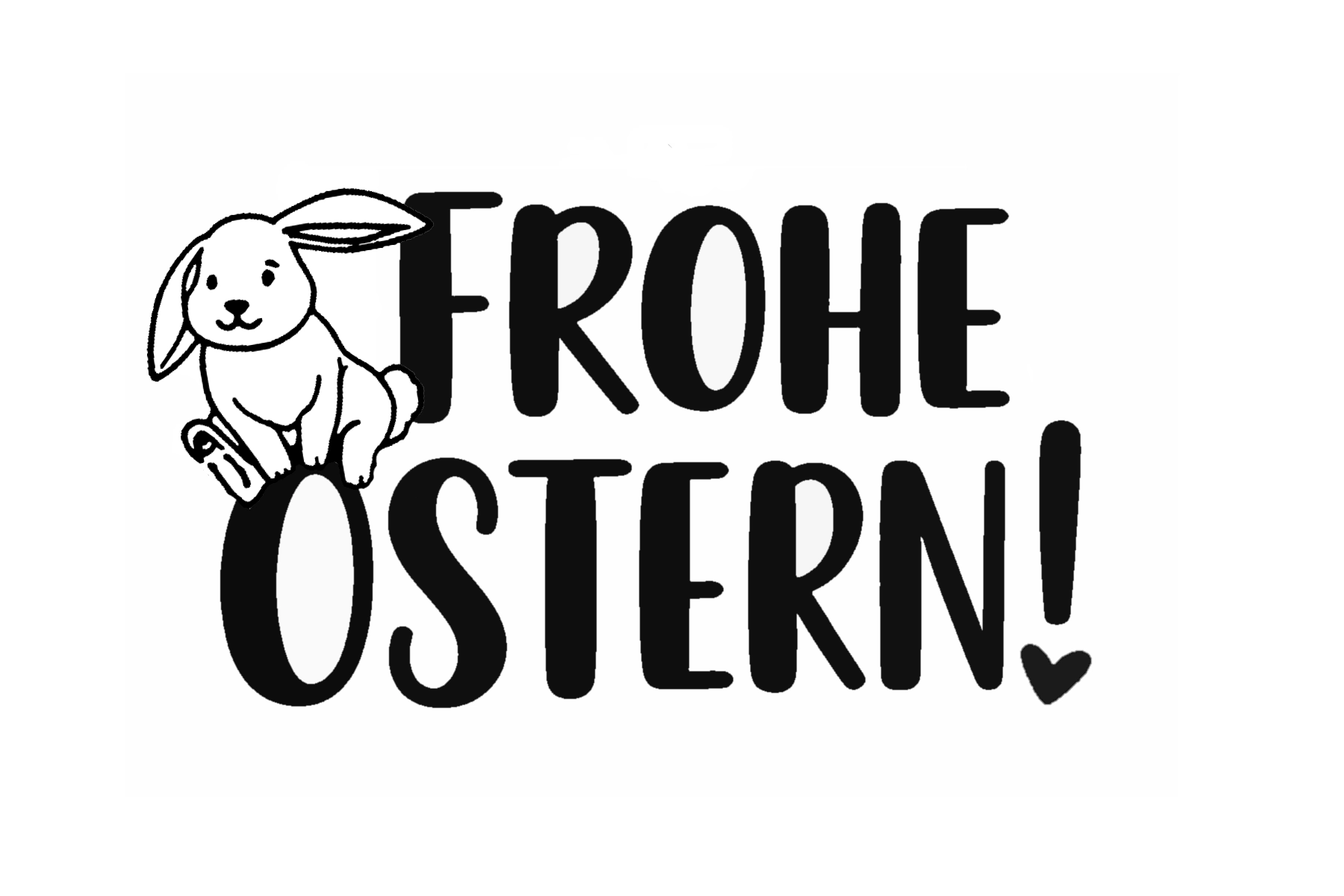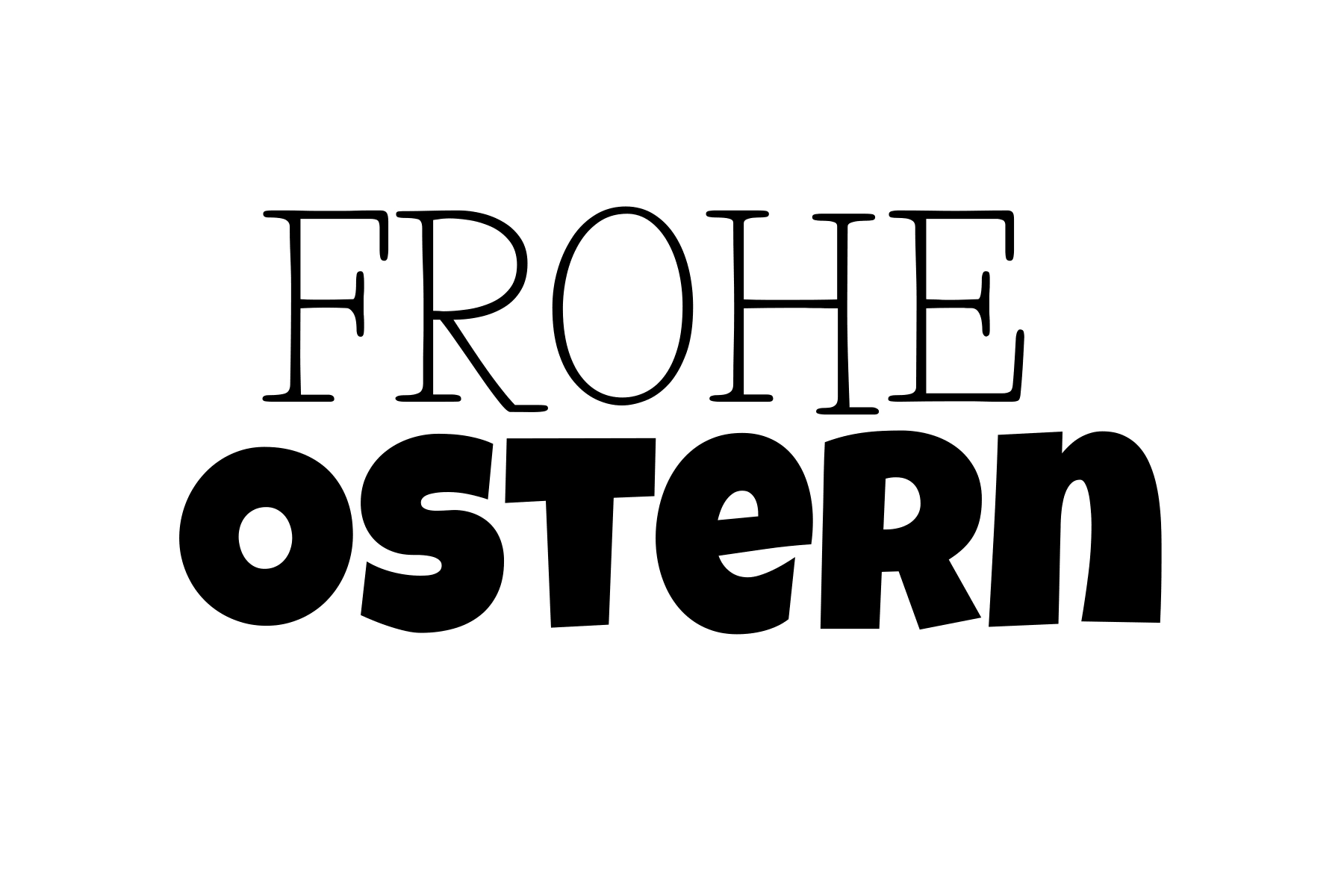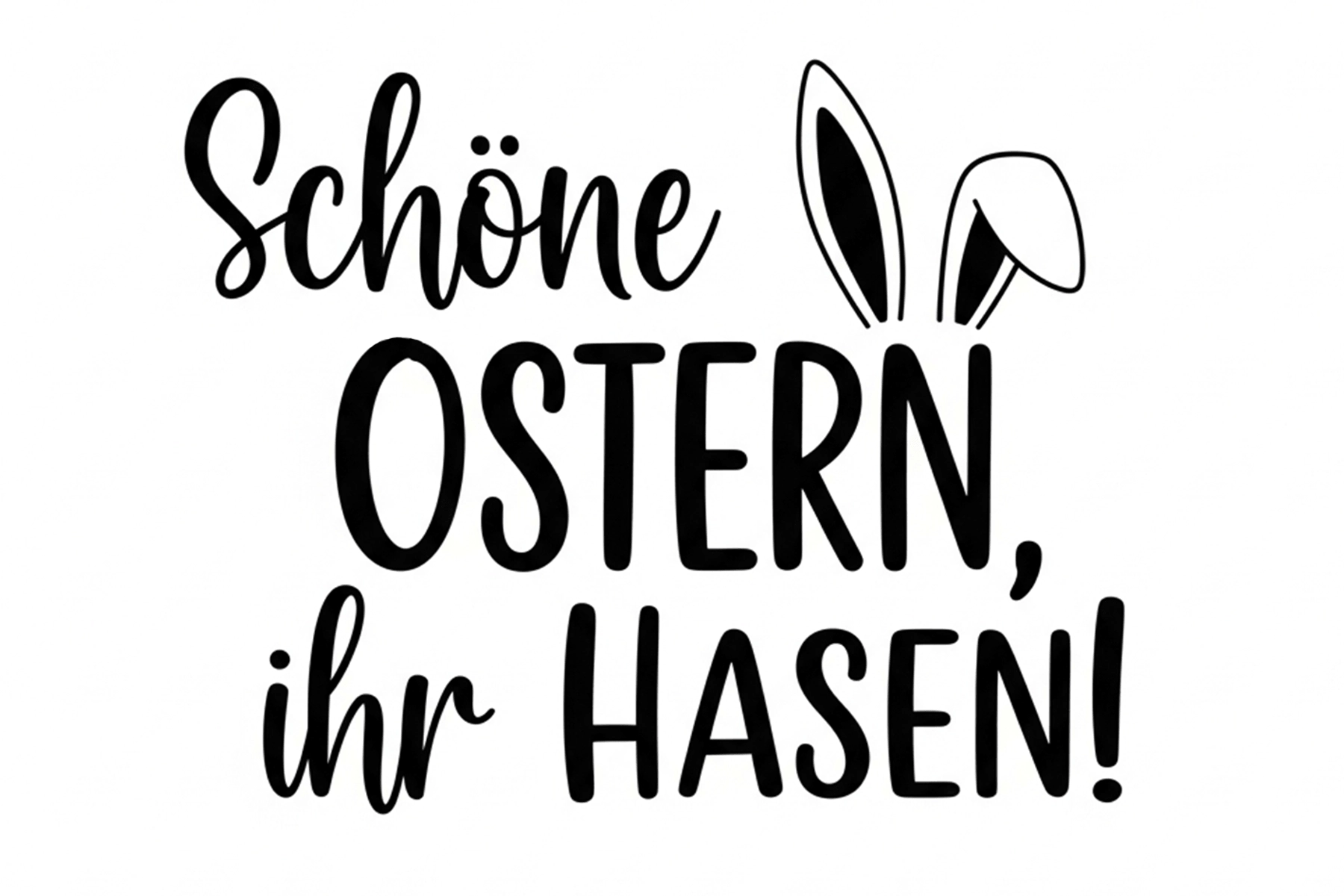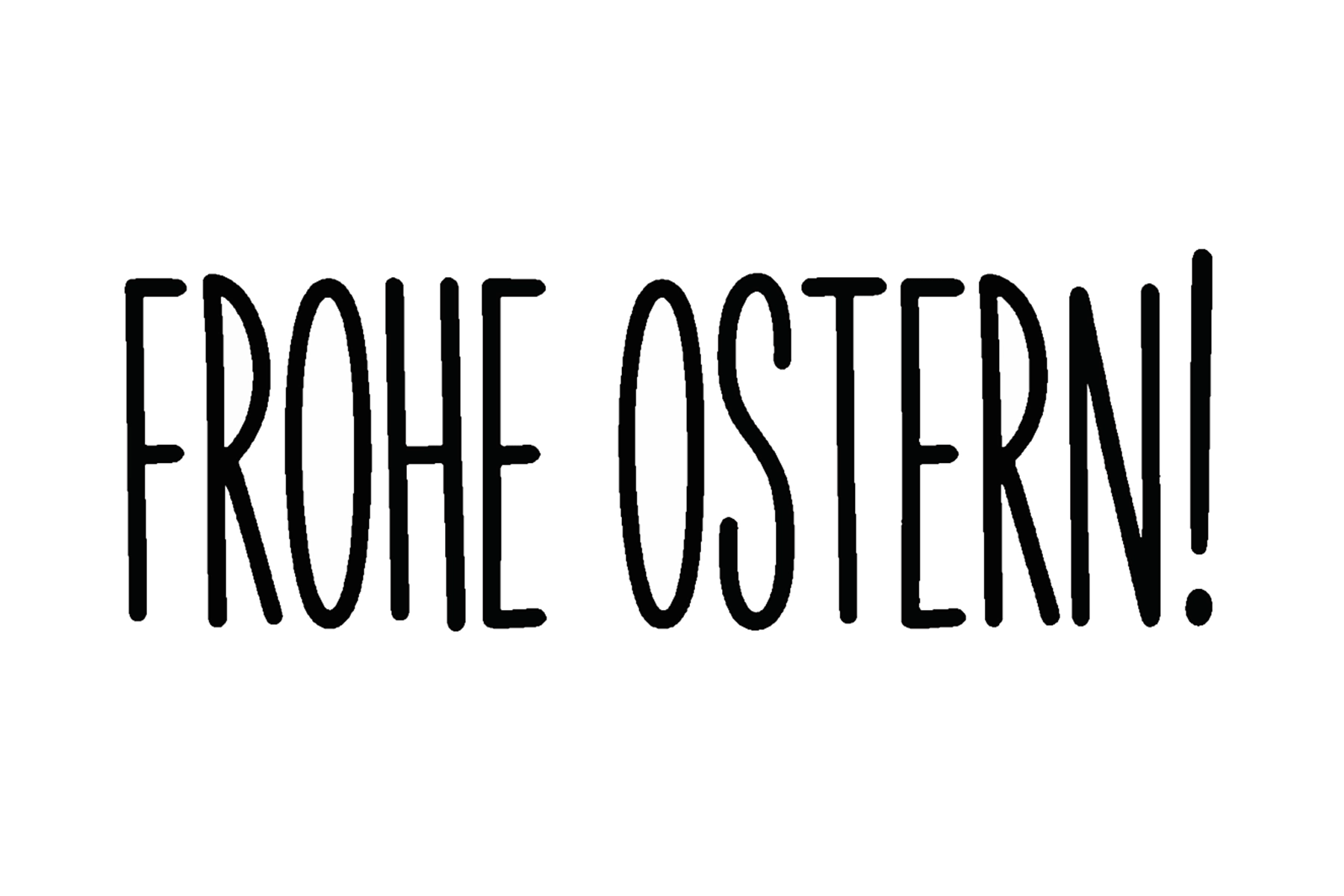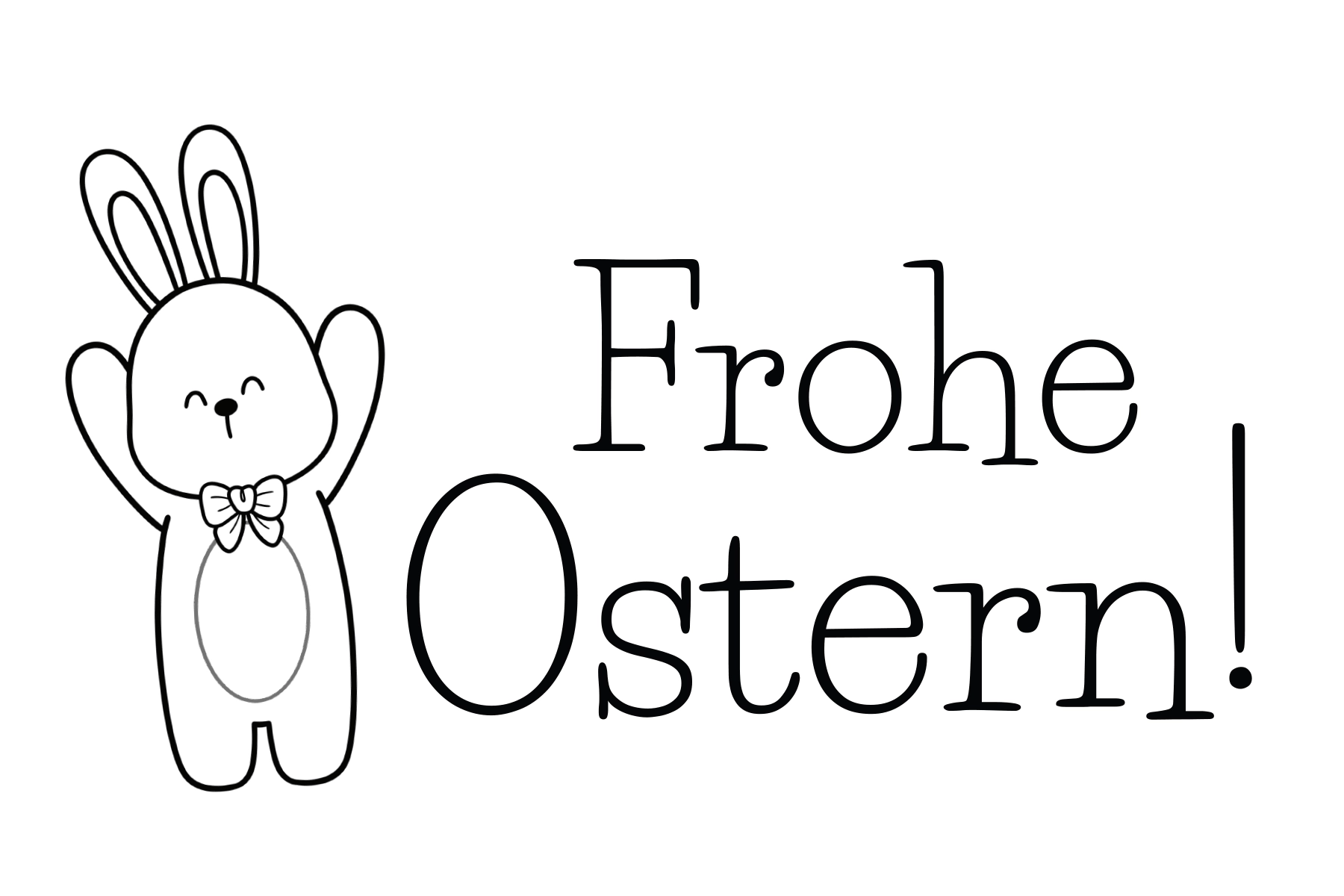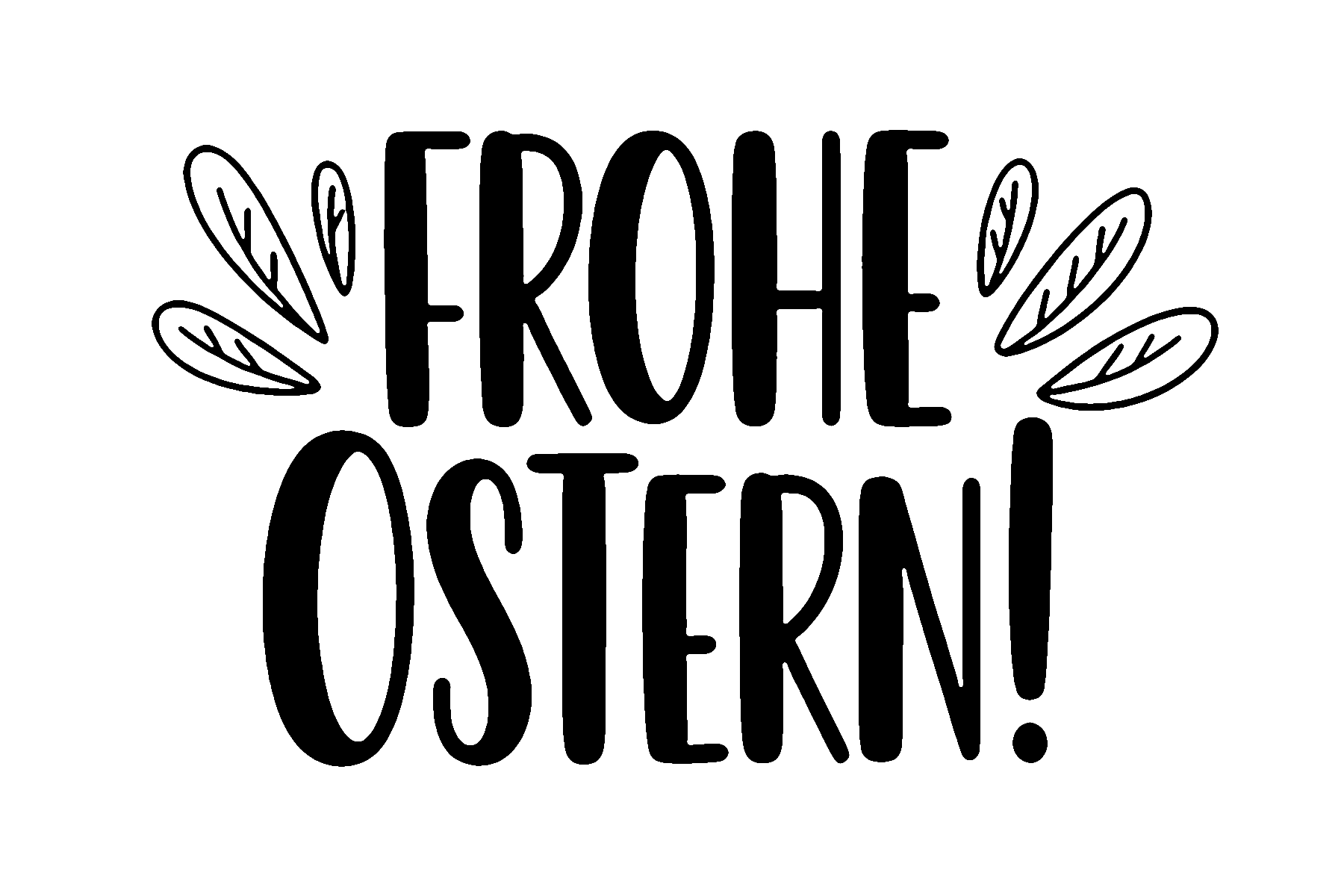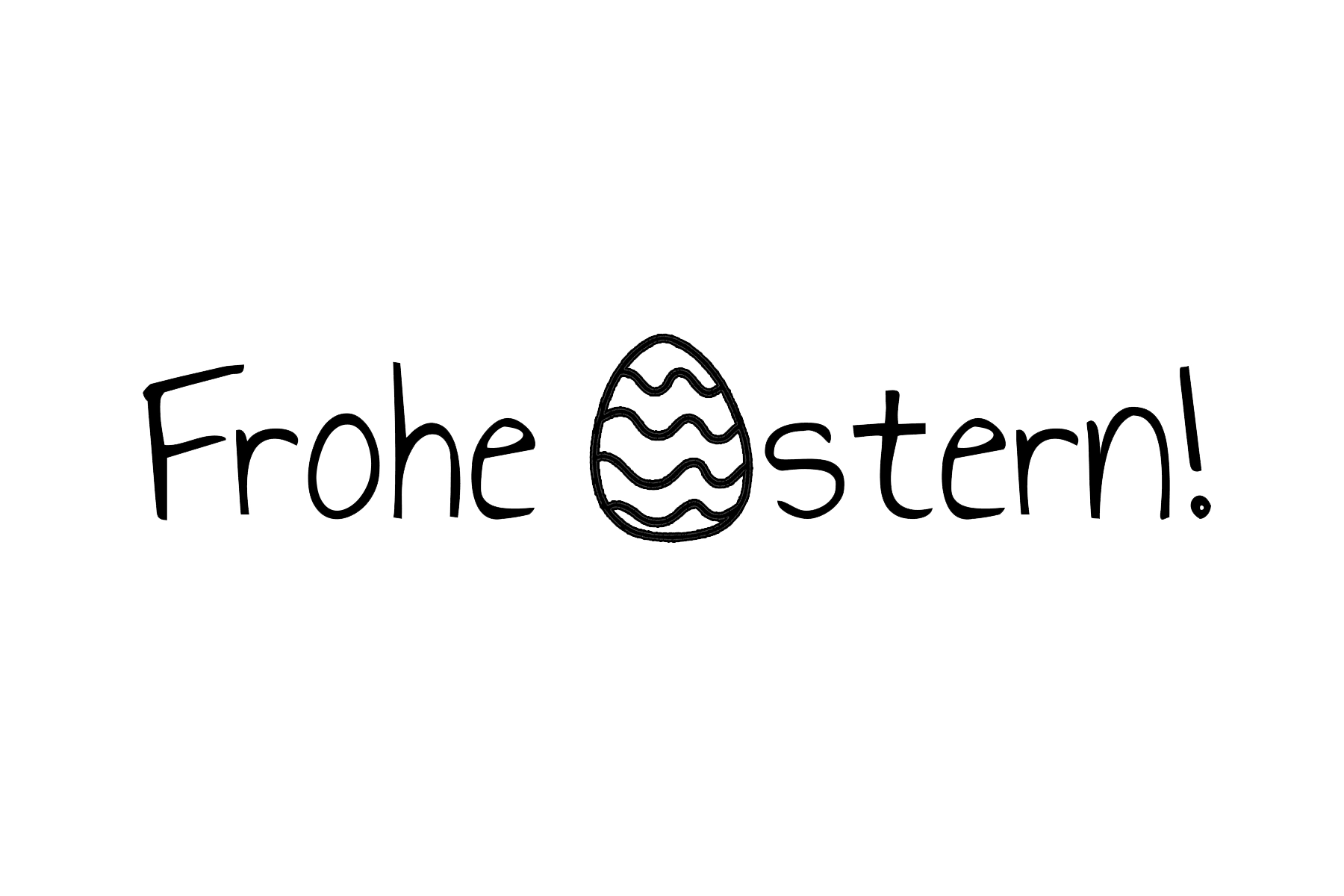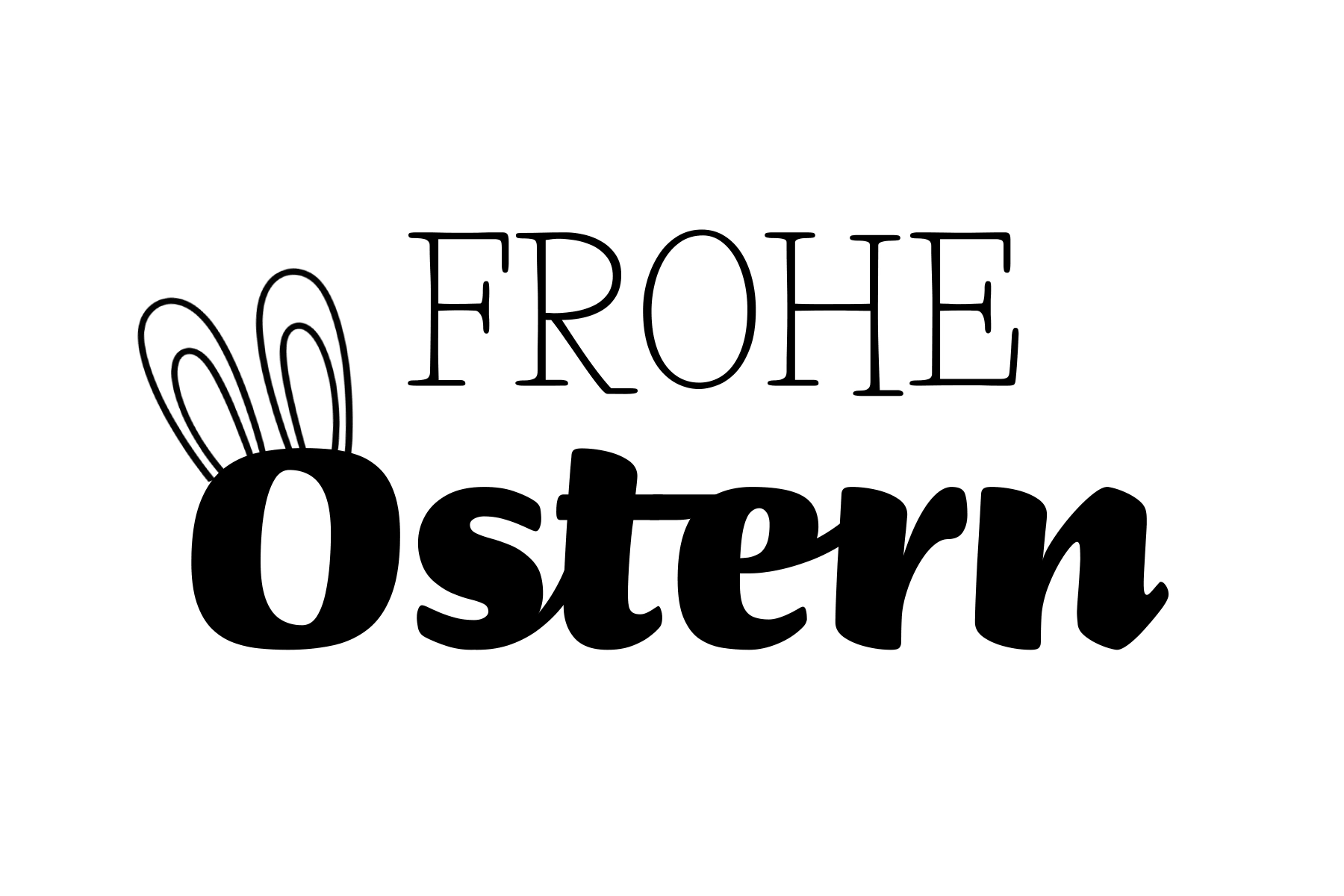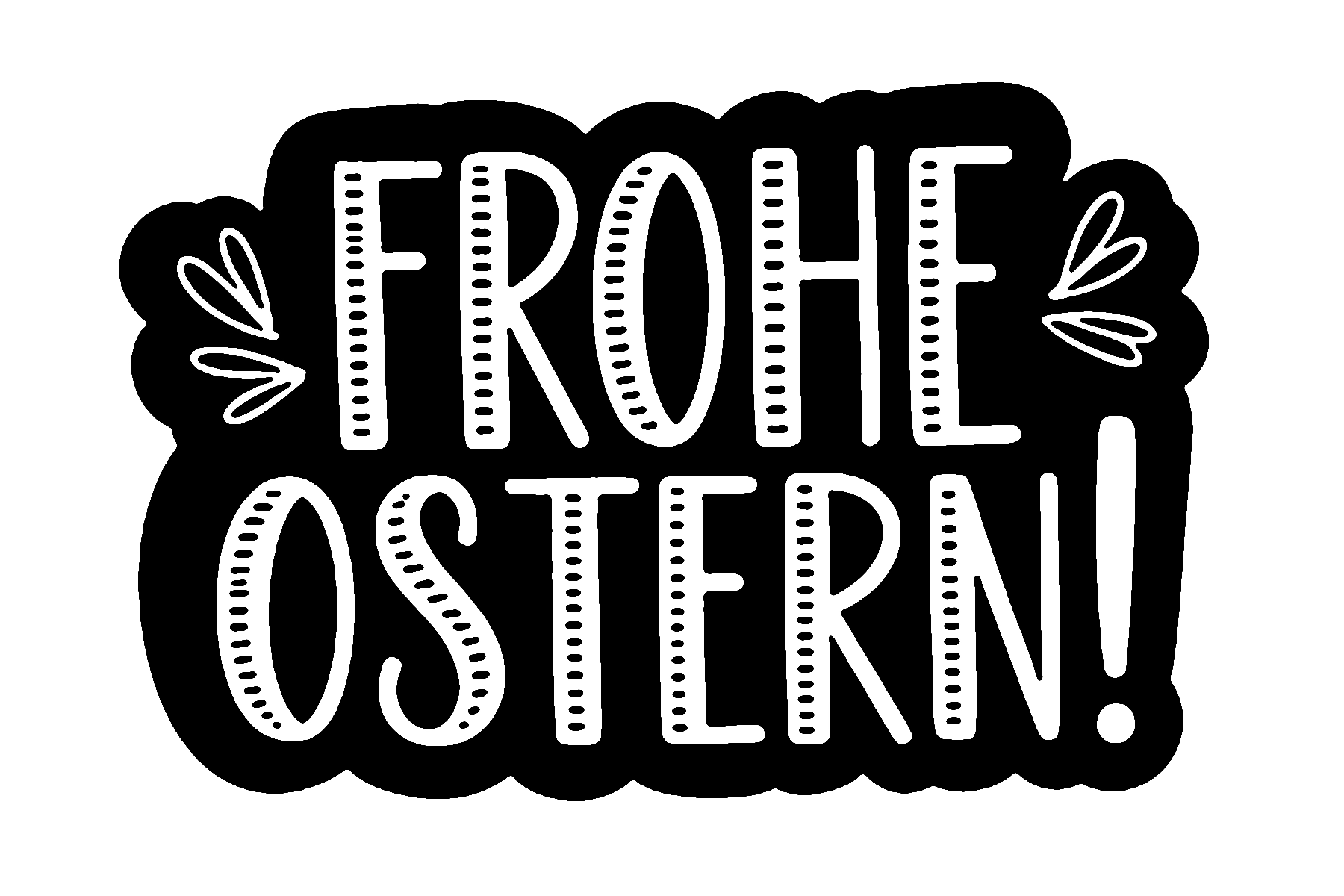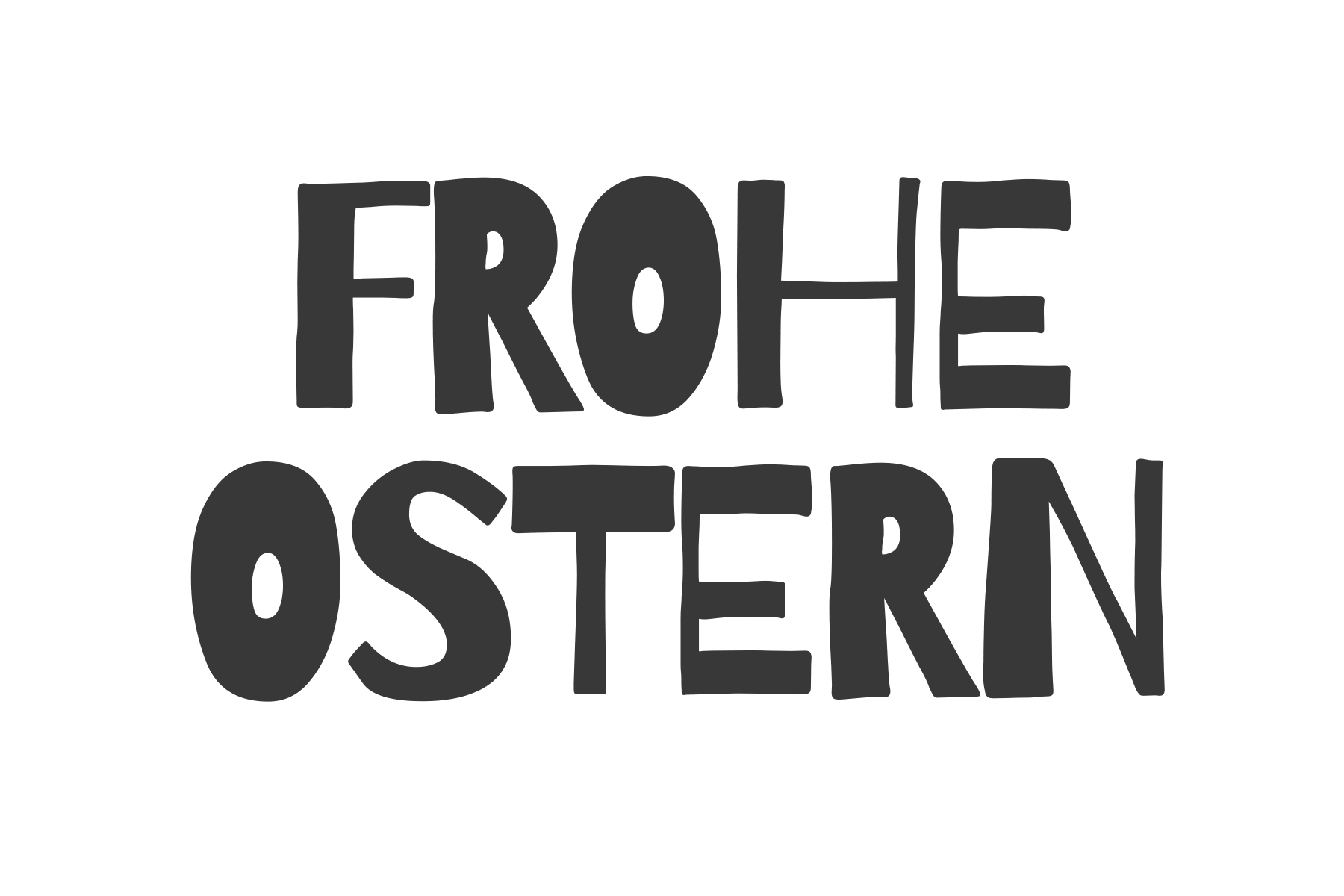
Frohe Ostern Schriftzug | kostenlose Vorlagen zum Ausdrucken
Passend zur Osterzeit findest du hier kostenlose Schriftzüge, um „Frohe Ostern“ zu wünschen.
Egal, ob du nach schwarz-weißen Schriftzügen als Vorlage für selbst gestaltete Karten, nach Malvorlagen oder nach bunten Schriftzügen zum Versenden suchst – wir haben den passenden Frohe-Ostern-Schriftzug.
Moderne Frohe-Ostern-Schriftzüge
Hier sind süße und moderne Frohe-Ostern-Schriftzüge, die sich perfekt für kreative und zeitgemäße Ostergrüße eignen.
Frohe-Ostern-Schriftzug: modern
Frohe Ostern Schriftzug
Frohe-Ostern-Schriftzug als Handlettering-Vorlagen
Diese Handlettering-Vorlagen eignen sich perfekt, um eigene Osterkarten zu gestalten oder das Schreiben dekorativer Schriftzüge zu üben.
Du kannst den gewünschten Frohe-Ostern-Schriftzug einfach ausdrucken und abpausen oder abzeichnen.
Frohe Ostern: Schriftzug-Vorlagen in Schwarz-Weiß
Frohe Ostern Schriftzug
Kalligraphie-Schriftzüge für Ostern
Elegante und geschwungene Schriftzüge im Kalligraphie-Stil verleihen deinen Ostergrüßen eine besonders edle und klassische Note.
Schöne Schreibschrift-Vorlagen für Ostern
Frohe Ostern Schriftzug
Bunte Frohe-Ostern-Schriftzüge im Clipart-Stil
Diese fröhlichen, bunten Schriftzüge sorgen sofort für Osterstimmung und eignen sich besonders gut zum Versenden oder für kreative Bastelprojekte.
Frohe-Ostern-Schriftzug: bunt
Frohe Ostern Schriftzug
Frohe Ostern: Schriftzug zum Ausmalen
Die folgenden Frohe-Ostern-Schriftzüge kannst du als Malvorlage ausdrucken und individuell gestalten.
Frohe-Ostern-Schriftzug: Malvorlagen
Frohe Ostern Schriftzug